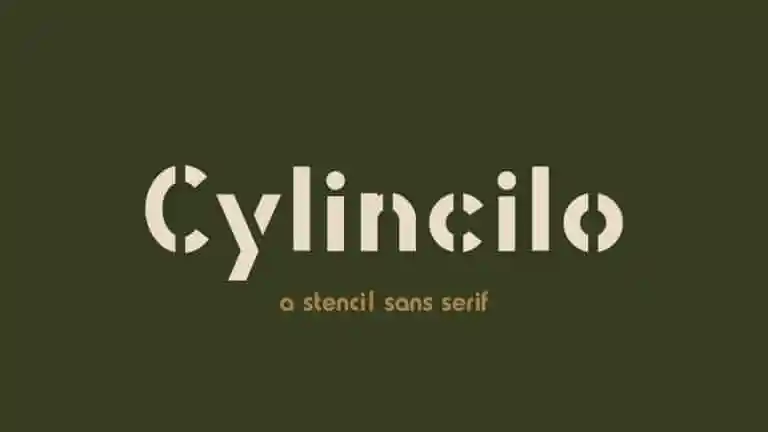
Cylincilo Display Font é uma elegante tipografia sans serif ideal para aplicações de marca e exibição. Desenvolvida pelo designer J Hudson, Cylincilo se destaca como um tipo stencil geométrico que captura o espírito de simplificação moderna. Este tipo deve ser usado em grande escala, especialmente nas matérias-chave ou aplicativos de postagem, onde pode desempenhar um papel vibrante e forte. Perfeito para aplicações visuais impactantes como cabeçalhos e aplicações decorativas, Cylincilo transmite uma modernidade minimalista. É perfeitamente adaptado para uso em banners, cartazes e até mesmo em materiais de marketing de grande porte, garantindo um visual único e contemporâneo que chamará a atenção do público. Se você está procurando por uma fonte sans serif que se destaca e consegue destacar sua marca ou mensagem de maneira assertiva e minimalista, Cylincilo é o tipo perfeito.